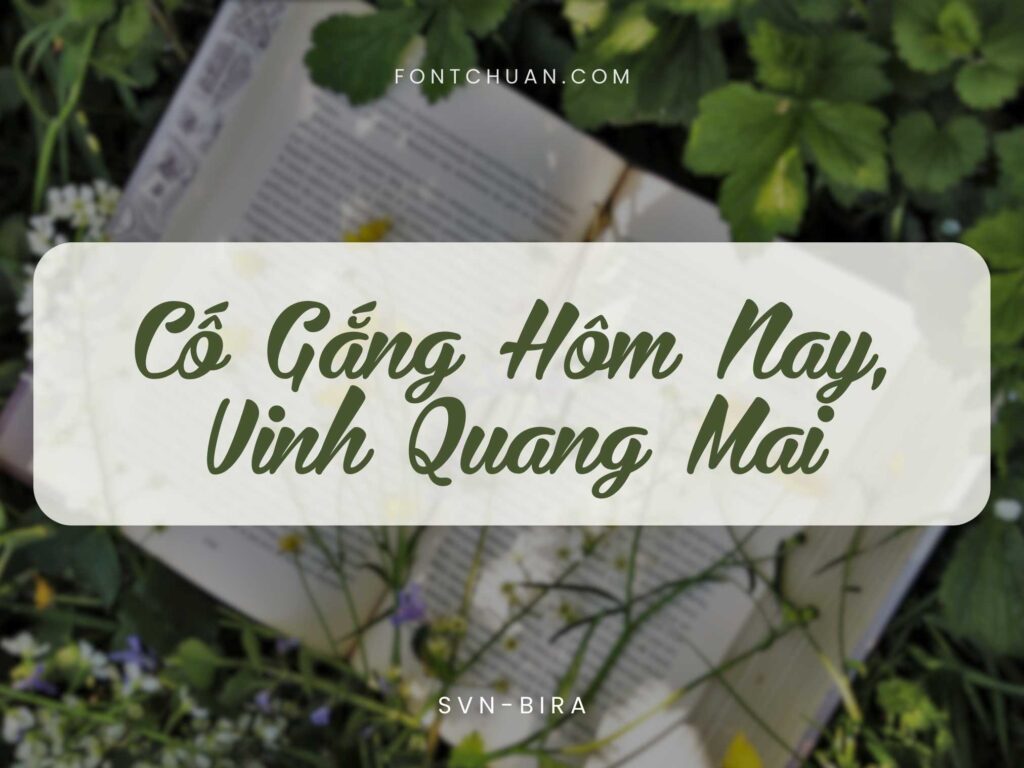
Font SVN Bira Việt Hóa
Bira là một font chữ script độc đáo, được thiết kế bởi Måns Grebäck và phát hành lần đầu vào năm 2012. Font này mang phong cách viết tay với các đường nét mượt mà và uyển chuyển, tạo nên sự thân thiện và gần gũi cho các thiết kế. Bira được thiết kế với chức năng OpenType nâng cao, đảm bảo chất lượng cao và hỗ trợ đa ngôn ngữ. Font đã được Việt hóa để hỗ trợ tiếng Việt bởi Styleno.1 Fonts, đồng thời hỗ trợ nhiều ngôn ngữ khác, giúp mở rộng phạm vi sử dụng trên toàn cầu. Font này được thành viên của Font Chuẩn sưu tầm và chia sẻ, đáp ứng nhu cầu của bạn đọc và ứng dụng thực tế vào các dự án thiết kế.
Đặc điểm thiết kế của Bira bao gồm các đường nét viết tay mềm mại, tạo cảm giác tự nhiên và thân thiện. Font này phù hợp cho các ứng dụng như thiết kế logo, tiêu đề, nhãn mác và các dự án sáng tạo khác. Các ngành nghề phù hợp bao gồm quảng cáo, nghệ thuật và thiết kế đồ họa.